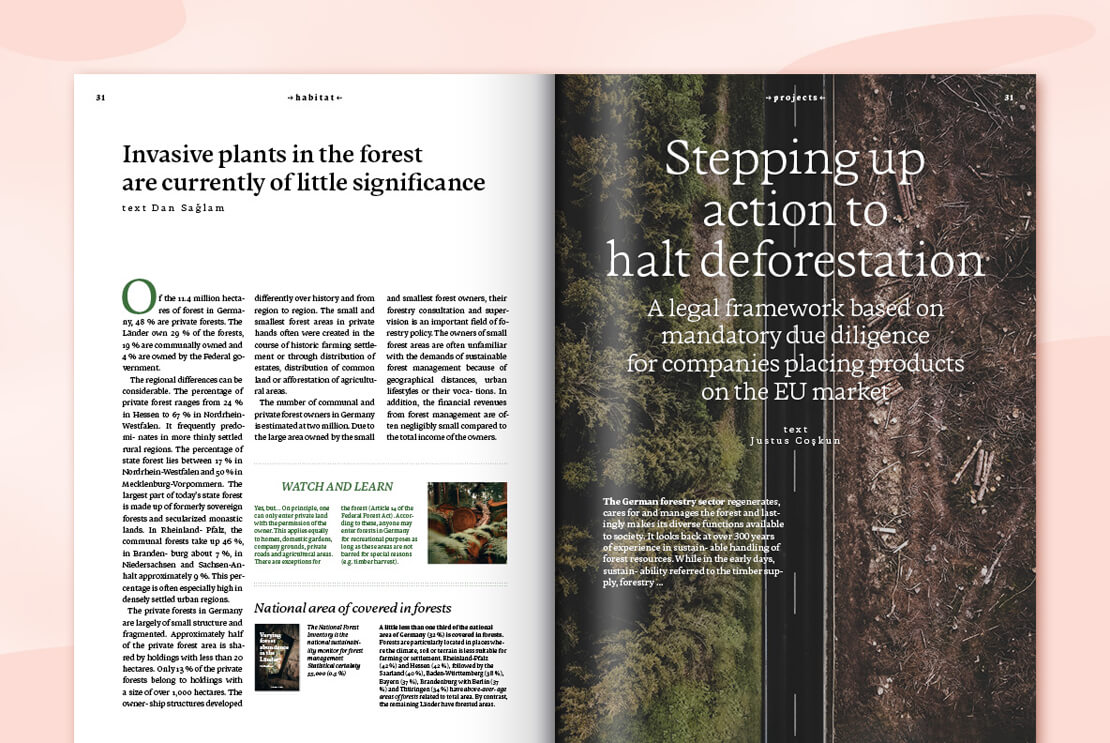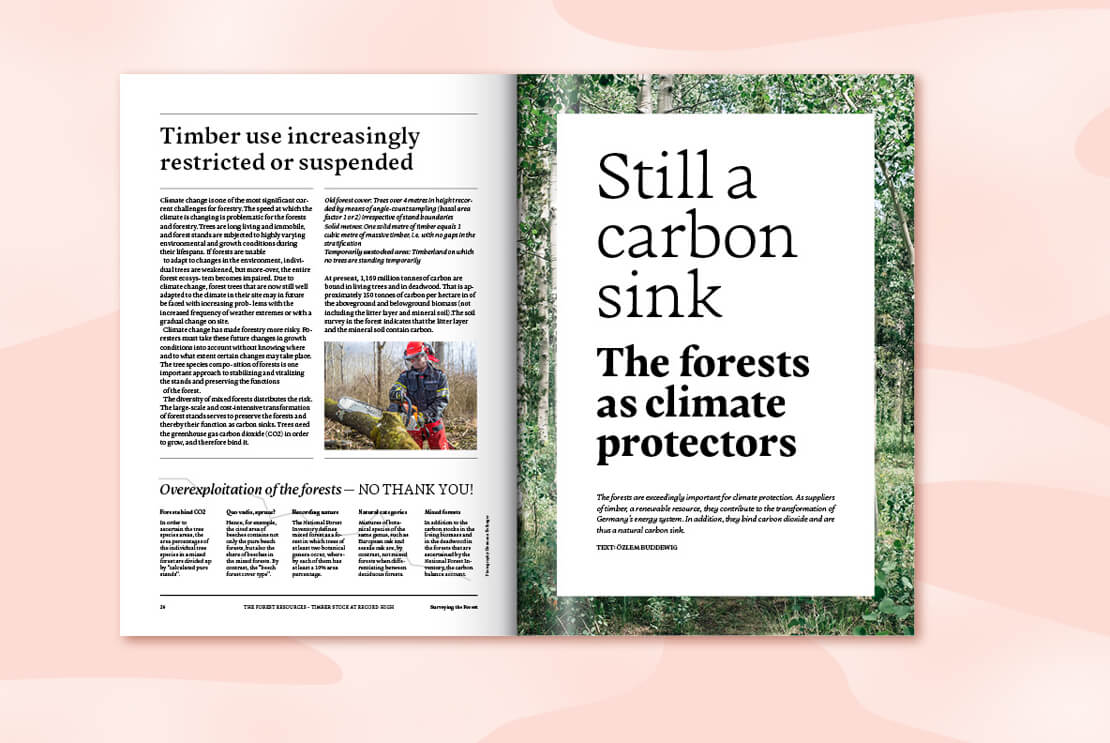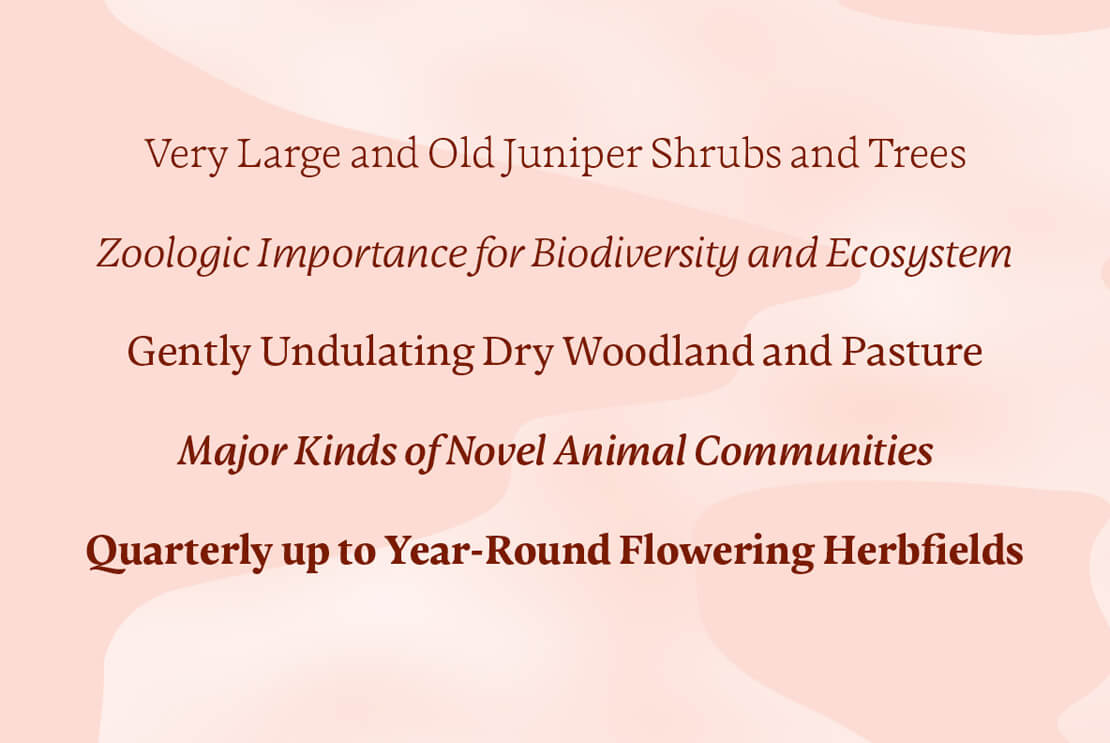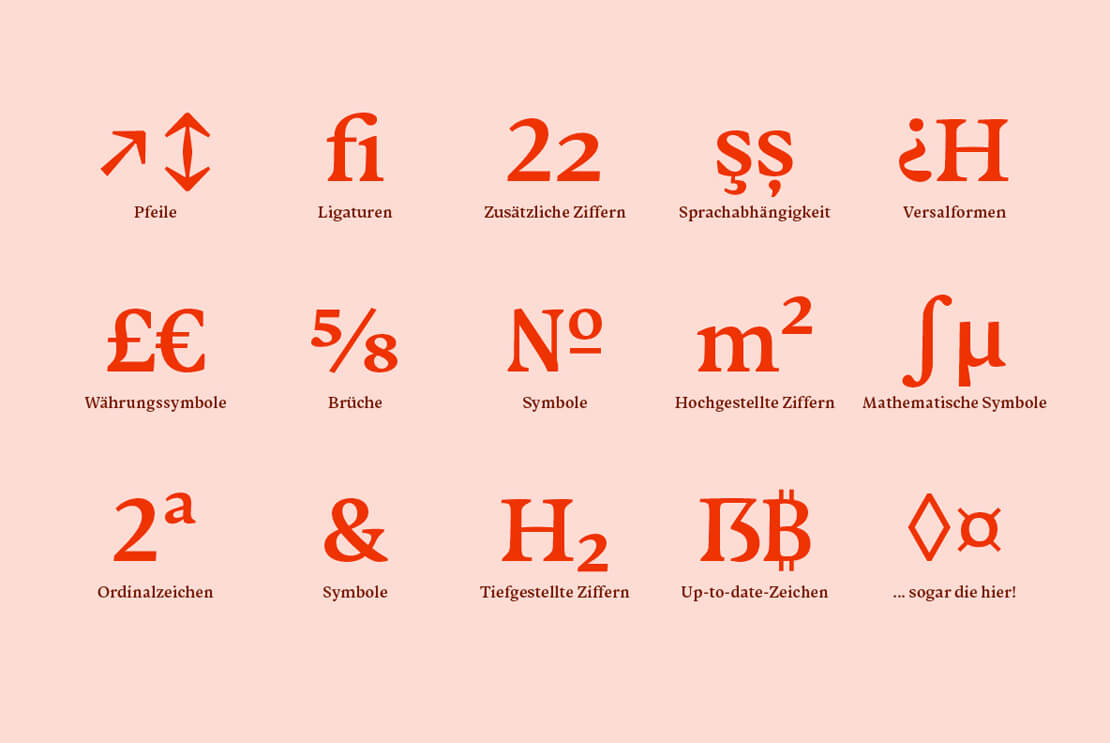
Adelbrook: Fest verwurzelte Serifenschrift
Mit der »Adelbrook« veröffentlicht Philip Lammert eine Schriftfamilie, die harmonischen Rhythmus bildet und Ruhe bewahrt – mit dynamischem Strich, asymmetrischen Serifen und in Leserichtung lehnenden Stämmen.
Entstehung der »Adelbrook«
Schriftgestalter Philip Lammert versuchte sich bereits im Oktober 2020 als Übung an einem schwungvollen Entwurf, der in sich dennoch eine Konstruiertheit wahrt. Das Gestaltungsprinzip mit dem nach oben hin schmaler werdenden Stamm übertrug er konsequent auf die gesamte Ausgestaltung. Die mit diesen klaren Regeln einhergehende Spannung fesselte ihn. Er überarbeitete daraufhin den Zeichensatz mehrfach, bis alle Details eine Textschrift mit zeitgenössischer Schärfe ergaben.
10 Schnitte, 5 Strichstärken und 543 Schriftzeichen
Die Schriftfamilie umfasst außerdem fünf feste Strichstärken von »Light« bis »Bold« sowie entsprechende Kursive. Wie alle Schriftarten von Philip Lammerts Type-Design-Studio Vibrant Types, ist auch die »Adelbrook« als Variable Font erhältlich, womit sich das Schriftgewicht stufenlos verstellen lässt.
Mit 543 Schriftzeichen bieten die Fonts zudem verschiedene Features wie Pfeile oder alternative Ziffern und Versalformen.